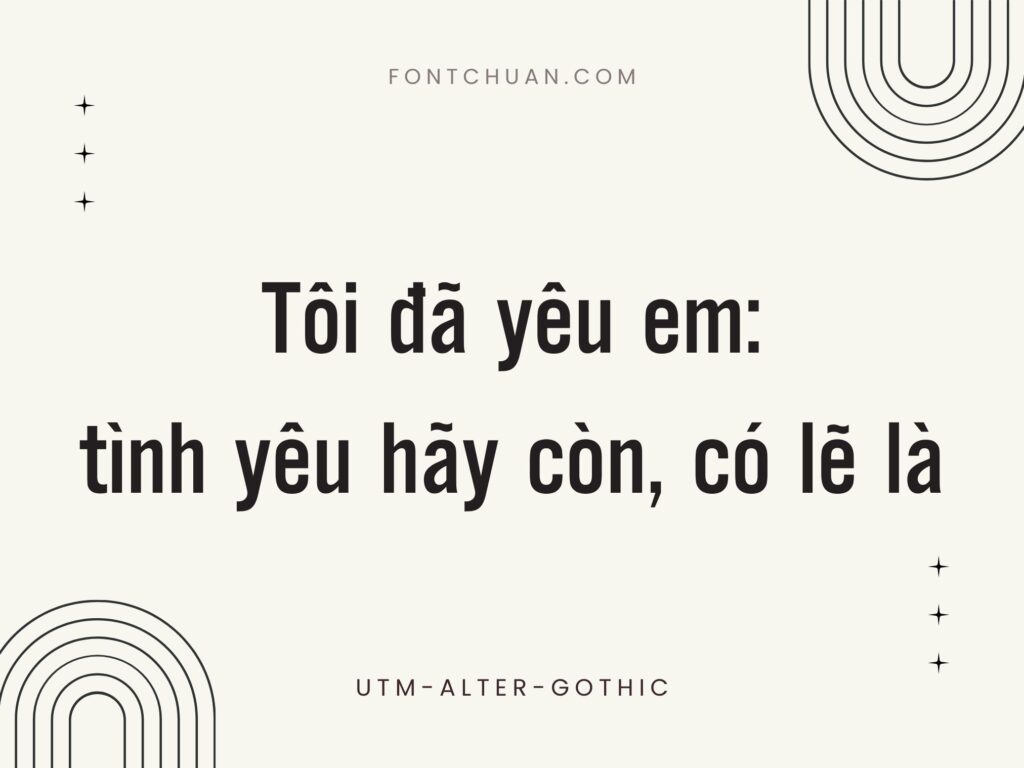
Font UTM Alter Gothic Việt Hóa
UTM Alter Gothic là một kiểu chữ Font Gothic cổ điển, mang phong cách mạnh mẽ và bí ẩn. Font này đã được Việt hóa, hỗ trợ đầy đủ tiếng Việt cùng hơn 100 ngôn ngữ khác. Thành viên của Font Chuẩn đã sưu tầm và chọn lọc font này nhằm đáp ứng nhu cầu đa dạng của bạn đọc và ứng dụng thực tế vào các dự án thiết kế.
UTM Alter Gothic có cấu trúc chữ với các nét dày và góc cạnh, tạo nên vẻ đẹp mạnh mẽ và cổ điển. Font này phù hợp cho các ứng dụng như thiết kế logo, tiêu đề, bao bì sản phẩm và các ấn phẩm in ấn. Các ngành nghề như quảng cáo, bất động sản, giáo dục và công nghệ có thể tận dụng UTM Alter Gothic để tạo điểm nhấn độc đáo trong thiết kế.